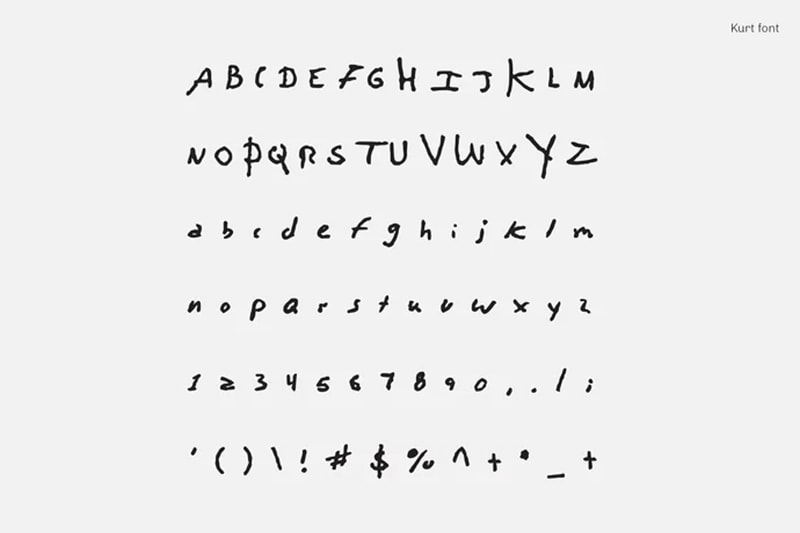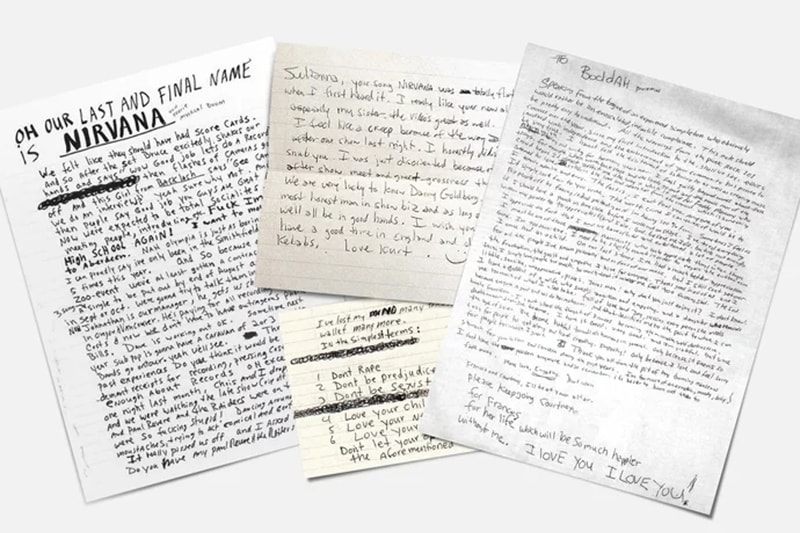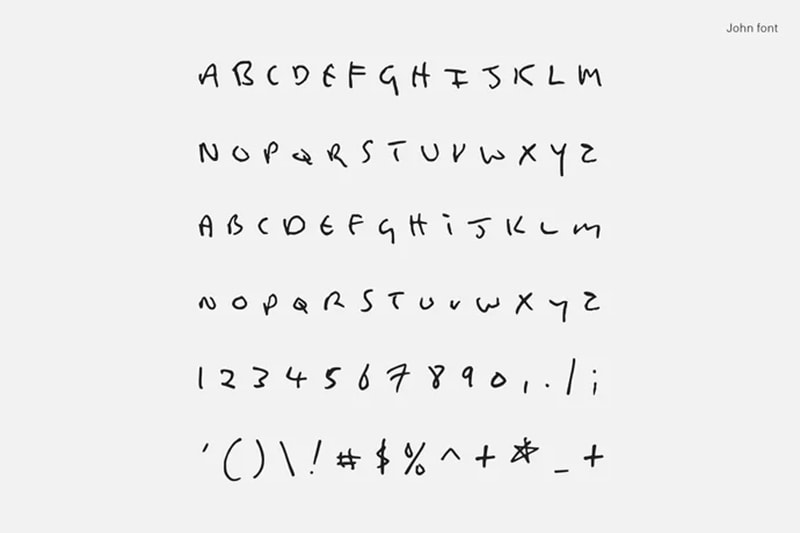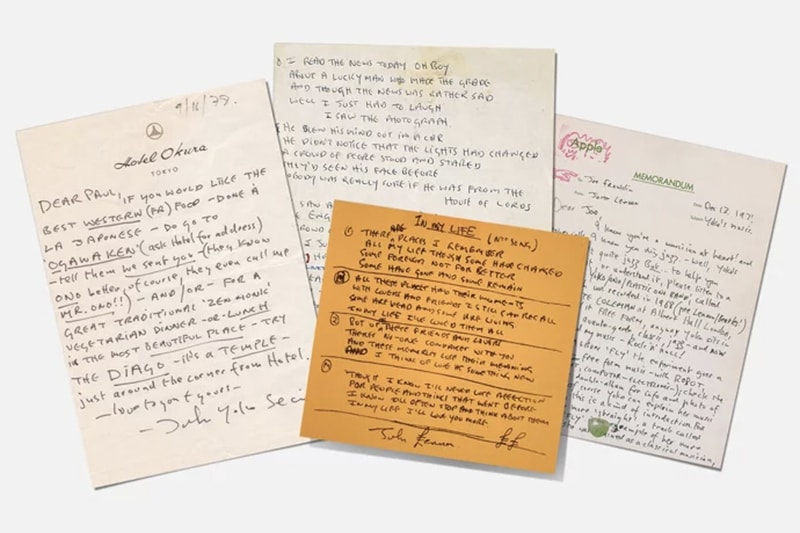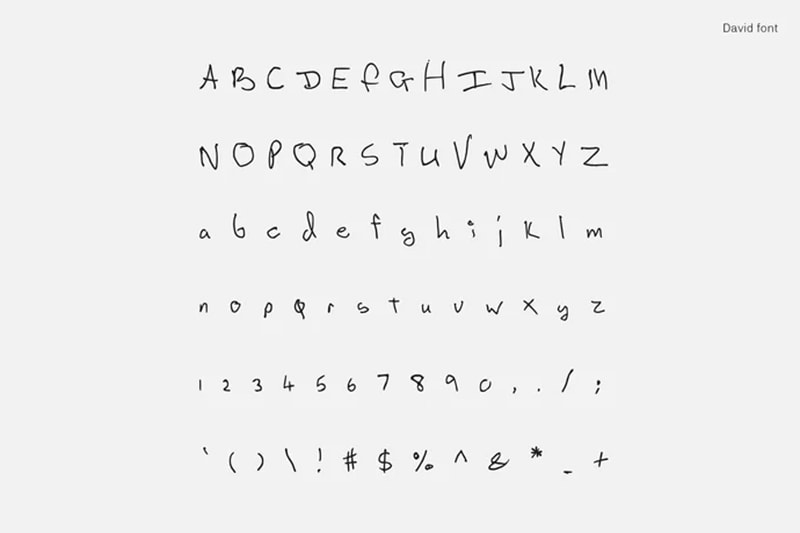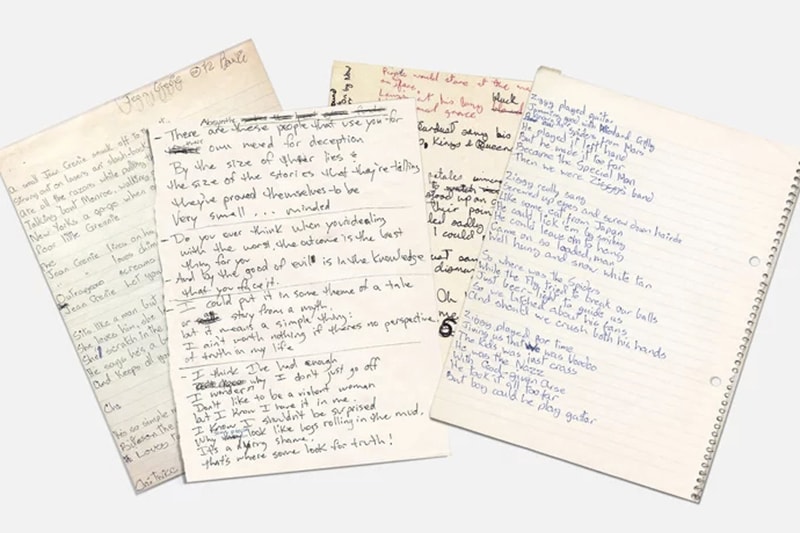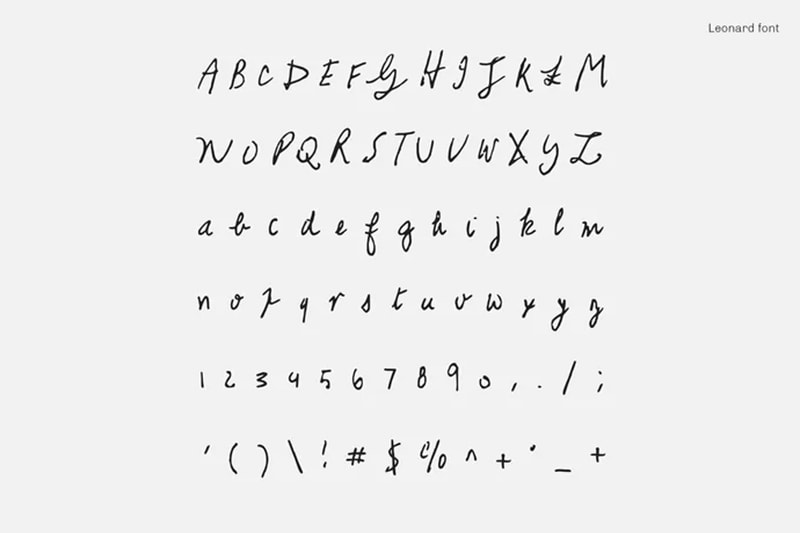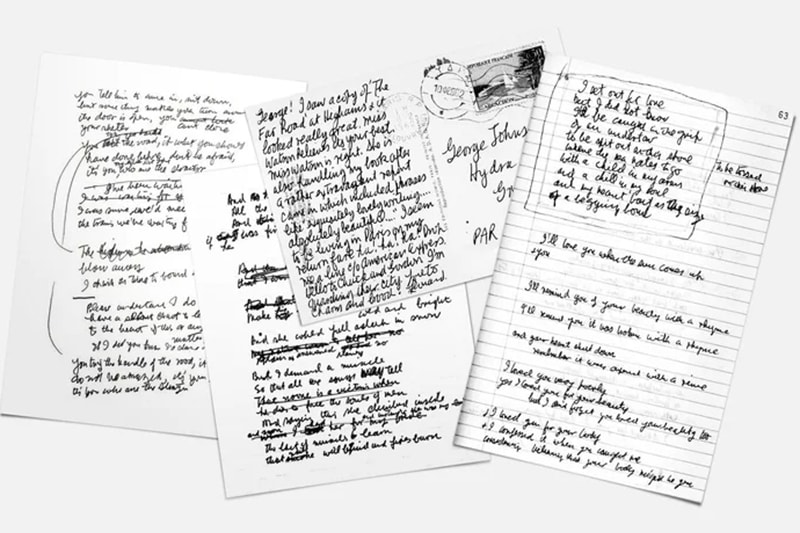
Kurt Cobain 等逝世樂人的字體目前可供下載
Kurt CobainDavid BowieJohn LennonLeonard Cohen 等已故音樂人除了留給後是無限的音樂貢獻之外,他們在時裝、藝術等領域也有莫大的影響。近日,設計師 Nicolas Damiens 和 Julien Sens 便參考了以上四位音樂人的筆跡,創作出一系列可以下載使用的字體。他們以這些人的筆記、信件以及 Kurt Cobain 的遺書為範本,設計出了特別的字樣,甚至表示 Kurt Cobain 的字體充滿詩意。不過也有網友表示這兩位設計師毫不尊重亡者,不曉得各位如何看待此事?當然,有意下載這些字體的朋友我們也為你準備好了連結